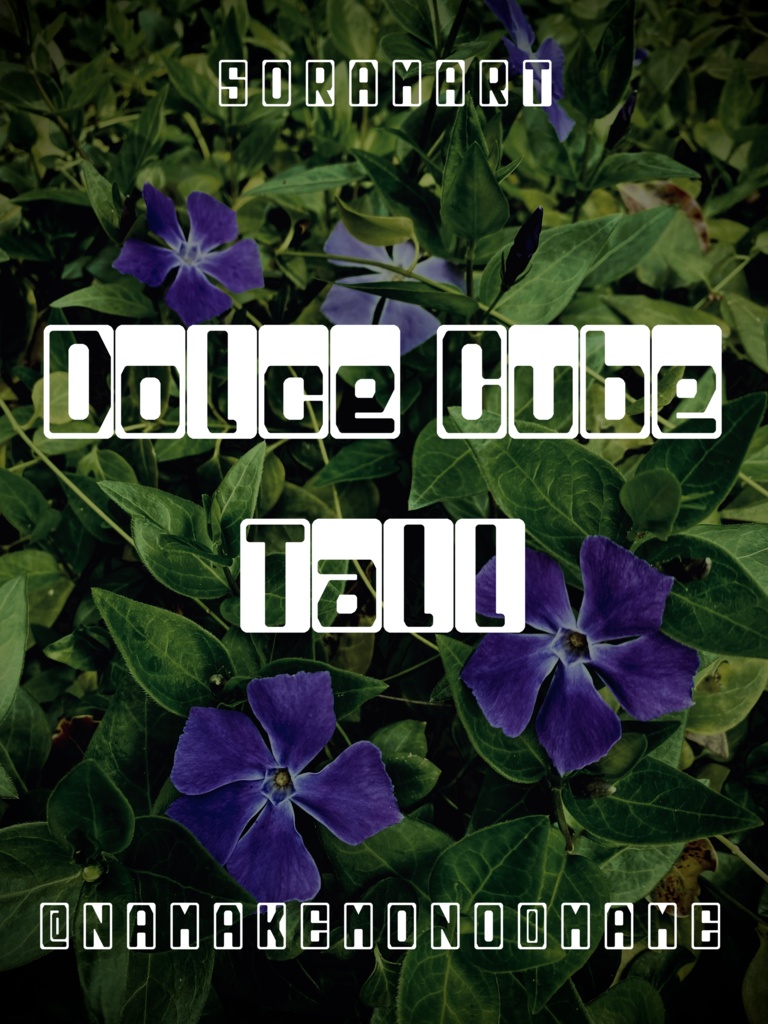
そらマートフォントデータ”Dolce Cube Tall”ダウンロード商品¥ 2,500カートに入れるギフトとして贈る「ギフトとして贈る」とはコロコロっとした可愛らしいスタンプ風縦長白抜きフォント "Dolce Cube Tall" です。 「TrueTypeフォントファイル」という形式です。 ダウンロードした後、Zipファイル内のデータをインストールしてお使いください。 このフォントは商用利用可となっております。 お客様の制作・創作活動のお役に立てれば幸いです。 ※使用上の注意事項などは、添付のReadmeをお読みください。そらマートFANBOX開設中フォント・書体フォントデータ”RANMMA Drive”そらマート¥ 0フォント・書体フォントデータ”Dandy Laser Max”そらマート¥ 2,500フォント・書体フォントデータ”Dandy Laser”そらマート¥ 2,500フォント・書体フォントデータ”Bubblegum Beat”そらマート¥ 2,500フォント・書体フォントデータ”Caltrop Serif LLL”そらマート¥ 2,500フォント・書体フォントデータ”Caltrop Serif LL”そらマート¥ 2,500フォント・書体フォントデータ”Caltrop Serif”そらマート¥ 2,500フォント・書体フォントデータ”Tonik Crate Super Long”そらマート¥ 2,500フォント・書体フォントデータ”Dot Eat Bug Acid”そらマート¥ 2,500フォント・書体フォントデータ”Dot Eat Bug Mild”そらマート¥ 2,500フォント・書体フォントデータ”Dot Eat Bug”そらマート¥ 2,500フォント・書体フォントデータ”Solid Voltage Strike”そらマート¥ 2,500フォント・書体フォントデータ”Solid Voltage”そらマート¥ 2,500フォント・書体フォントデータ”Henge Edge Rock”そらマート¥ 2,500フォント・書体フォントデータ”Henge Edge Tall”そらマート¥ 0フォント・書体フォントデータ”Henge Edge”そらマート¥ 0フォント・書体フォントデータ”Chisel Stroke Wide”そらマート¥ 2,500フォント・書体フォントデータ”Chisel Stroke”そらマート¥ 2,500フォント・書体フォントデータ”Crushed Can Serif Empty”そらマート¥ 2,500フォント・書体フォントデータ”Crushed Can Serif Wide”そらマート¥ 2,500もっと見る